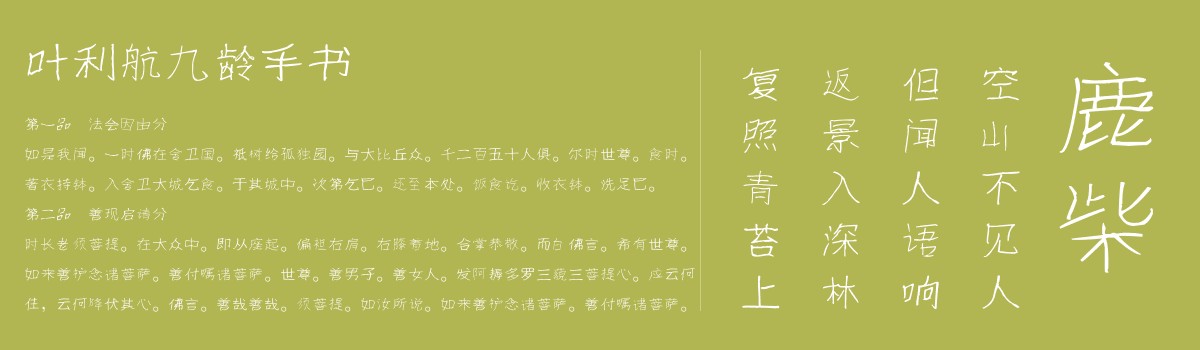
叶利航是叶根友的儿子,已经九岁了,故取名叶利航九龄手书,是一款九岁小孩书写的字体,这么多年来,一直想出一套真正意义上的小孩子字体,自己也曾刻意的去模仿小孩子的笔法和感觉去写字体,比如叶根友童体、叶根友小京楷字体等,都是在这种念想中去模仿孩童字体风格,但是始终不如意,今年暑假的时候,跟儿子商量,能不能书写一套字稿?于是,放弃了他暑假的时间,终于完成了这字体的书写,当然,作为奖励,特别带他去北京旅游。